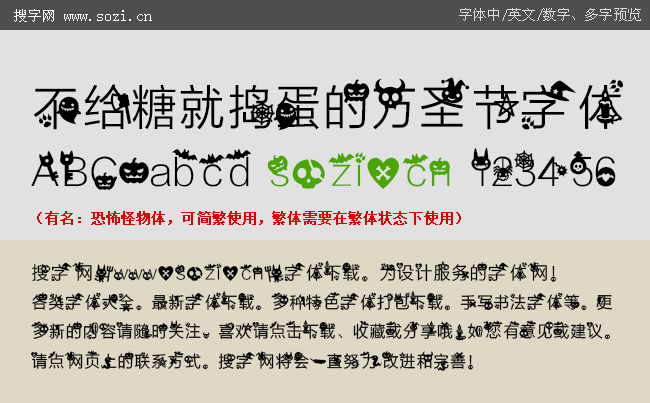
不給糖就搗蛋的萬圣節(jié)字體
搜字網(wǎng)給大家提供一款不給糖就搗蛋的萬圣節(jié)字體手機中文字體下載。這款手機字體是以黑體字體為原形,筆畫間嵌入了卡通怪物圖案。在具備黑體清晰端正的風(fēng)格同時,卡通味也特別濃,是一款很有趣的卡通字體,特別適合喜歡手機字體個性一些的朋友在手機上安裝使用。